40 бесплатных шрифтов «от руки»
В отличии от обычных шрифтов, шрифты “от руки” не смотрятся слишком строго, но они дают возможность лучше контактировать с посетителем сайта. Такие шрифты могут отлично смотреться в дизайне, придать ему определенный стиль и креативный вид. Несколько примеров применения таких шрифтов вы сможете увидеть в ранее опубликованной подборке 23 художественных сайта.
Тут вы найдете 40 отличных шрифтов “от руки”, которые сможете загрузить и использовать в своих работах абсолютно бесплатно, перейдя по ссылке над шрифтом.
Шрифт Alpha Mack
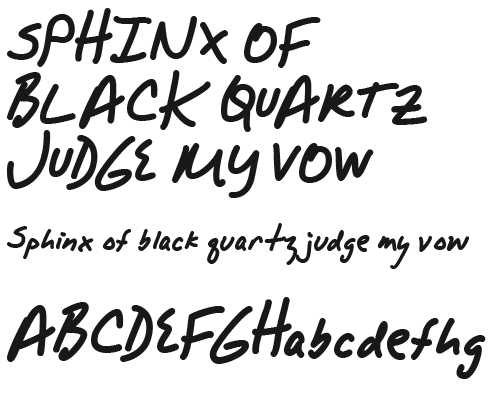
Шрифт под названием Analgesics
Шрифт Bubbly Frog
Шрифт под названием Christopher Hand
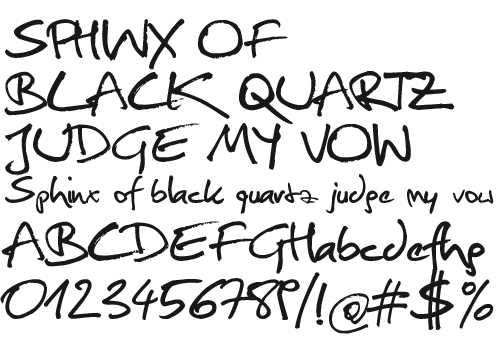
Отличный прописной шрифт Dali
Шрифт “от руки” Fabulous 50s
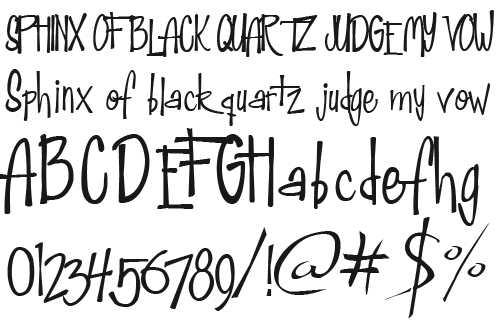
Обведенный шрифт Fail
Зарисованный шрифт FFF Tusj
Шрифт Daniel
Шрифт под названием Note this
Отличный прописной шрифт Pisan
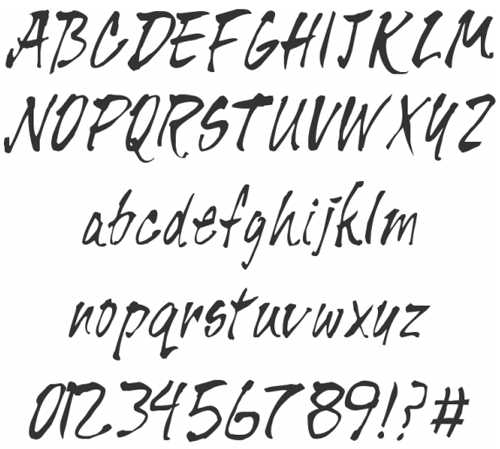
Шрифт “от руки” Rabiohead
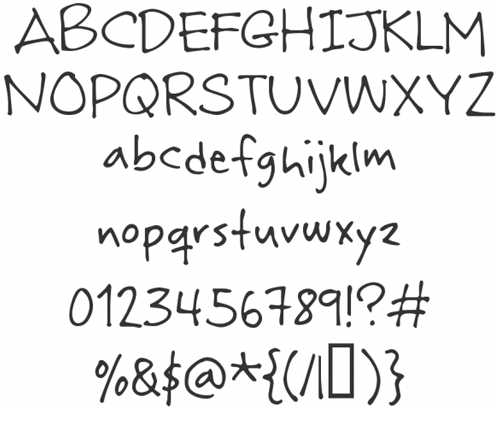
Креативный шрифт Glider Girls
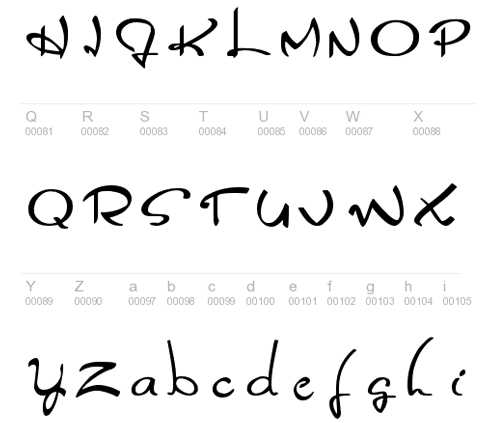
Шрифт в стиле гранж Green Piloww
Шрифт под названием Grutch Shaded
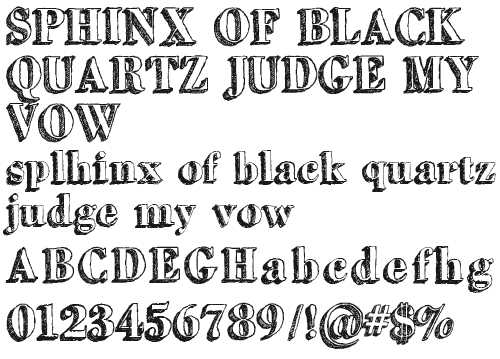
Жирный прописной шрифт Hand of Sean
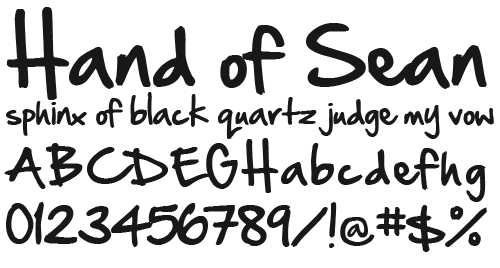
Гранжевый шрифт HandVetica
Шрифт Jamaistevie
Прописной шрифт под названием James Fajardo
Креативный шрифт Estrya’s Handwriting
Шрифт “от руки” Jerry’s handwriting
Прописной шрифт Joe Hand 2
Аккуратный шрифт Journal
Шрифт под названием Just Me Again Down Here
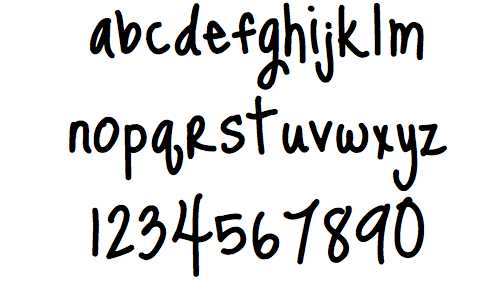
Шрифт Later On
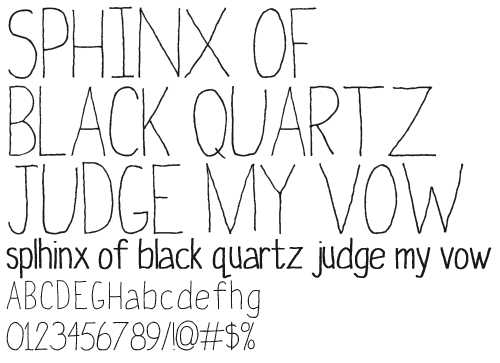
Жирный шрифт “от руки” Love Ya Like A Sister
Шрифт “от руки” с завитками Luna Bar
Наведенный шрифт Mia’s Scribblings
Креативный шрифт “от руки” Pappo’s Blues Band
Наведенный шрифт в стиле гранж Peixe Frito
Шрифт Positiv-A
Шрифт с черепами Rock Show Whiplash
Шрифт Salamander
Жирный прописной шрифт Sophie, Regular
Еще один шрифт в стиле гранж The Quiet Scream
Шрифт Thurston Erc
Знаки и буквы различных размеров в шрифте Two Turtle Doves
Шрифт WC RoughTrad Bta
Креативный прописной шрифт Windsong
Кликаем «OK» — появляется след. окно.
В этом окне откройте картинку с вашими буквами. Выделите буковку «А», скопируйте её и вернитесь в FontCreator, откройте ячейку с буквой «F» и вставьте туда свою букву. Красные пунктирные линии можно передвигать, расставьте их так, как показано на следующем рисунке.
Буква должна стоять на линии (Baseline) и НЕ должна вылезать за верхнюю горизонтальную линию (WinAscent), а также НЕ должна вылезать за нижнюю горизонтальную линию (WinDescent), иначе она будет обрезана. Вертикальная левая линия должна стоять на том месте, где буква начинается, а вертикальная правая линия – где буква заканчивается. Если буква вылезет за вертикальные линии, то при печатании будет наложение одной буквы на другую, это тоже нам не подходит.
Сейчас объясню, почему букву «А» мы вставили в ячейку с буквой «F». Данная программа предназначена для создания шрифтов, использующая латинские буквы. Нам же напротив нужно изготовить шрифт для русских букв. Поэтому сделанный нами РУССКИЙ шрифт получится на ЛАТИНСКОЙ раскладке. Для того чтобы было удобнее, будем вставлять русские буквы в ячейки с латинскими буквами, в соответствии с клавиатурой.
Простой прописной шрифт Monika
Шрифт прописью Pavane
Жирный шрифт прописью One Fell Swoop
Ровный аккуратный шрифт Scrypticali
Аккуратный прописной шрифт Old Script
Шрифт прописью с завитками Freebooter Script
Красивый ровный прописной шрифт Brock
Размазанный шрифт Selfish
Жирный шрифт Ballpark Weiner
Тонкий шрифт Precious font
Кривой шрифт Killigraphy font